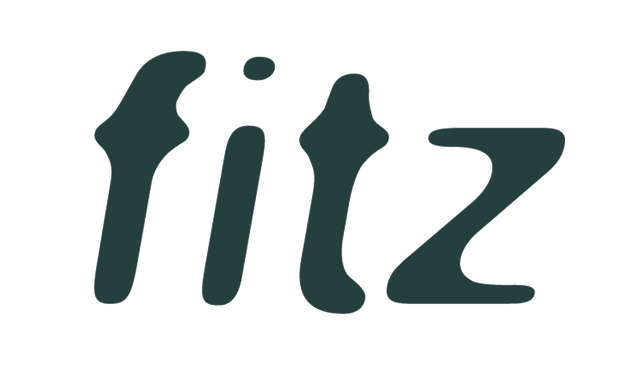
... formlos:
Als Versuch eines Klones der FF-Blur wurde Gaussian Blur Italic passen:
Du kannst es aber auch mal mit einer Helvetica Italic ausprobieren. Zuerst mal ein Rasterbild erzeugen. Auf dieses läßt Du den Gaussfilter los und vektorisierts das ganze wieder. Falls Du mal Lust und Zeit hast ...